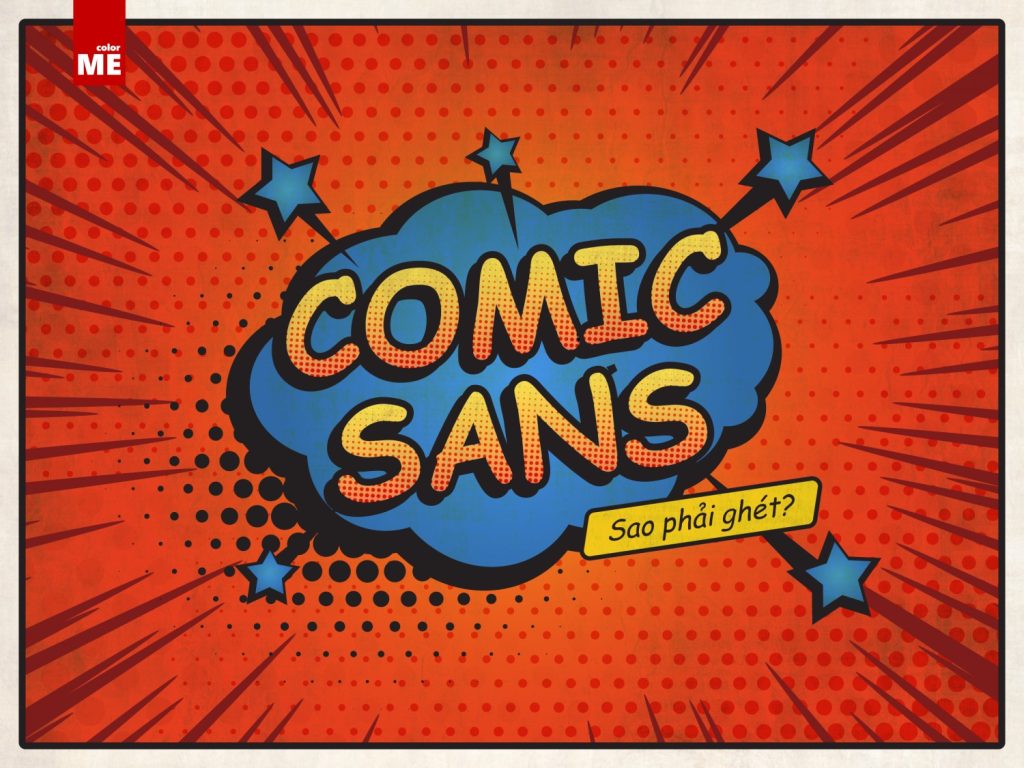
Font Comic Sans Việt Hóa
Tác giả: Vincent Connare
Kiểu chữ: Comic Sans
Font Comic Sans Việt Hóa là phiên bản Việt hóa của phông chữ Comic Sans nổi tiếng, mang đến sự thân thiện và vui nhộn trong thiết kế. Font Comic Sans Việt Hoá là một font chữ thuộc bộ font chữ Việt Hoá. Với các ký tự được tùy chỉnh để hỗ trợ tiếng Việt, phông chữ này giữ nguyên phong cách mềm mại, ngộ nghĩnh và dễ đọc, phù hợp cho các dự án không chính thức, đặc biệt là liên quan đến trẻ em, thiệp mời, hoặc các ấn phẩm mang tính giải trí. Comic Sans Việt Hóa đem lại cảm giác gần gũi và dễ tiếp cận, giúp truyền tải thông điệp một cách nhẹ nhàng và thoải mái. Đây là lựa chọn lý tưởng cho những thiết kế cần sự vui tươi và thân thiện với người dùng.